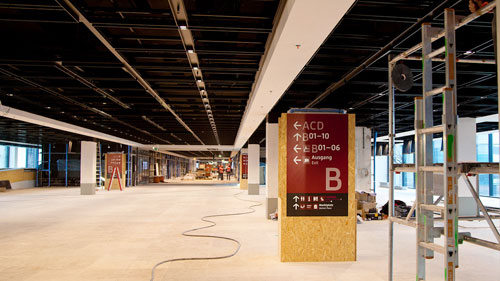
Über 1000 mal wurde das gestern (hier im Fontblog) angekündigte Video des 6. Berliner Creative Morning bereits angesehen. In ihrem 20-minütigen Referat stellen Heike Nehl und Sibylle Schlaich (Moniteurs, Berlin) das Leitsystem des neuen Airport Berlin Brandenburg vor. Ihre Arbeit setzt internationale Maßstäbe, den erstmals wurde ein Flughafen-Leitsystem mit allen seinen Komponenten – Design, Material, Schrift, Farbe, … – als zentrales identitätsstiftendes System in die Architektur und die Werbekommunikation eingebunden.
Oh Gott – diesen deutschen Akzent der beiden im Vortrag kann man kaum ertragen. Grauenhaft. Willkommen in der Provinz. Inhaltlich ist´s hier & dort interessant. Aber alles ein wenig hingebogen in der Hinleitung zur Umsetzung. Nicht überzeugend. Nach dem nächsten Urlaub wissen wir mehr.
Als gebürtige Niederländer muss ich auch noch mal kurz mein Senf dazugeben… Vielleicht ist es tatsächlich ein Idee um die video’s mit Untertitel zu versehen. Die beide Damen strengen sich (sichtbar) an Ihren Vortrag auf English zu halten, aber sind beide auch irgendwie super unsicher, aufgeregt und dan hilft es nicht wenn man alles auch noch in eine andere Sprache machen muss. Die Qualität der Präse hat mE wirklich unter gelitten, über den Inhalt kann man (wie auch schon Passiert bei der vorherige Beitrag) natürlich diskutieren :)
Ich bin auch der Meinung das die gewählte Farbe irgendwie nicht kräftig und aufmerksam genug ist. Sie ist zwar schön, aber ob es auch wirklich Praktisch ist?
Ich hatte die Möglichkeit einer der sogenannten ORAT-Flughafen Tester zu sein. Und konnte mich fast frei in dem Check-in Terminal & der Gate Area B aufhalten.
Ich bin ziemlich überrascht wie an vielen Stellen diese vertretene Konsequenz nicht umgesetzt ist. Fast überall erkennt man das auf Symmetrie geachtete wird. Eklatant fallen da die Check-in Bereiche total raus. Die sind links mit 2 Reihen Holzoptik-Panelen und rechts mit einer Reihe verkleidet! Da fängt es an …
Die Holzoptik ist kaschiertes Funier auf Spanplatten und diese Idee das mittels Raster an die Wand zu bringen um möglichst flexibel zubleiben, erinnert an frühe Designerjahre.
Ich persönlich finde auch diese Holzmaserung ein Graus und hochwertig sieht es nicht aus.
Mir gefallen sehr viele Elemente aus dieser Präsentation. Zum Beispiel die schraffierten großen Buchstaben. Ich finde es ist eine tolle Möglichkeit, Typografie zu strukturieren, ohne die Farben aufzuhellen, was bei Rot immer schwierig ist.
Auf den Folien gefällt mir die Überblendung von Foto zu Icon. Schön dargestellt.
> diese Holzmaserung ein Graus
wie, bleibt das etwa so? ich dachte die aufsteller sind noch mit holz geschützt, weil es dort noch bauarbeiten gibt. jetzt bin ich allerdings etwas schockiert.
zu dem rest möchte ich mich noch nicht wirklich äußern, weil man das design einfach live erleben muss, einige beispiele in dem video fand ich etwas zu weit hergeholt, bzw. wirkten diese eher aufgesetzt, aber ich bleib erstmal optimistisch und schau mir alles live mal in einer ich-muss-den-flieger-kriegen-situation mal an.
hatte heute nur kurz in den nachrichten was gehört, es verlief wohl alles reibungslos, allerdings gab es probleme bei der orientierung …
was auch immer das heißen soll.
ok, jetzt hab ich mir nochmal die bilder auf der moniteurs-webseite angesehen. *schockbeiseite* ich dachte echt du redest von dieser spanplattenoptik, wie oben im bild aber diese scheint doch nur der schutz zu sein, die richtigen tafeln haben dann diese dunkle holzmaserung, was ich persönlich erstmal ganz ansprechend finde. dadurch wirkt der flughafen nicht so kühl. gerade in diesem bezug finde ich den frankfurter flughafen schrecklich. die rasterelemente finde ich eine legitime lösung, aber wie gesagt ich war selbst noch nicht drinnen.
Informieren ist besser als phantasieren (Danke, Robert). Wer den Film und mein ausführlich beschriftetes Flickr-Fotoalbum gesehen hat, weiß: Im Moment ist am BER Airport Berlin Brandenburg noch kein einziges Hinweisschild im Original bzw. im Originalzustand zu sehen: guckst Du hier. In die Wände integrierte Hinweise sind noch nicht hinterleuchtet, frei stehende und hängende Wegweiser sind Dummies, damit die wertvollen Originalmöbel geschont werden – noch ist der Flughafen eine staubige Baustelle, mit 5000 Arbeitern und hunderten von Maschinen und Fahrzeugen, die Schaden anrichten können.
Zur englischen Sprache. Bezeichnenderweise kommen die Belehrungen nie von »native english speakern«, sondern meist von deutschen Oberlehrern, die sich selbst nie trauen würden, auch nur einen Satz vor Publikum in Englisch auszusprechen. Würden sie es hin und wieder tun, hätten sie Respekt vor einer solchen Übung, zumindest aber Verständnis für Holprigkeiten, und kämen nie auf die Idee, dies öffentlich zu kritisieren. Umso leichter fällt es ihnen, unter dem Schutz der Anonymität und aus dem heimischen Arbeitssessel abzulästern. Arm!